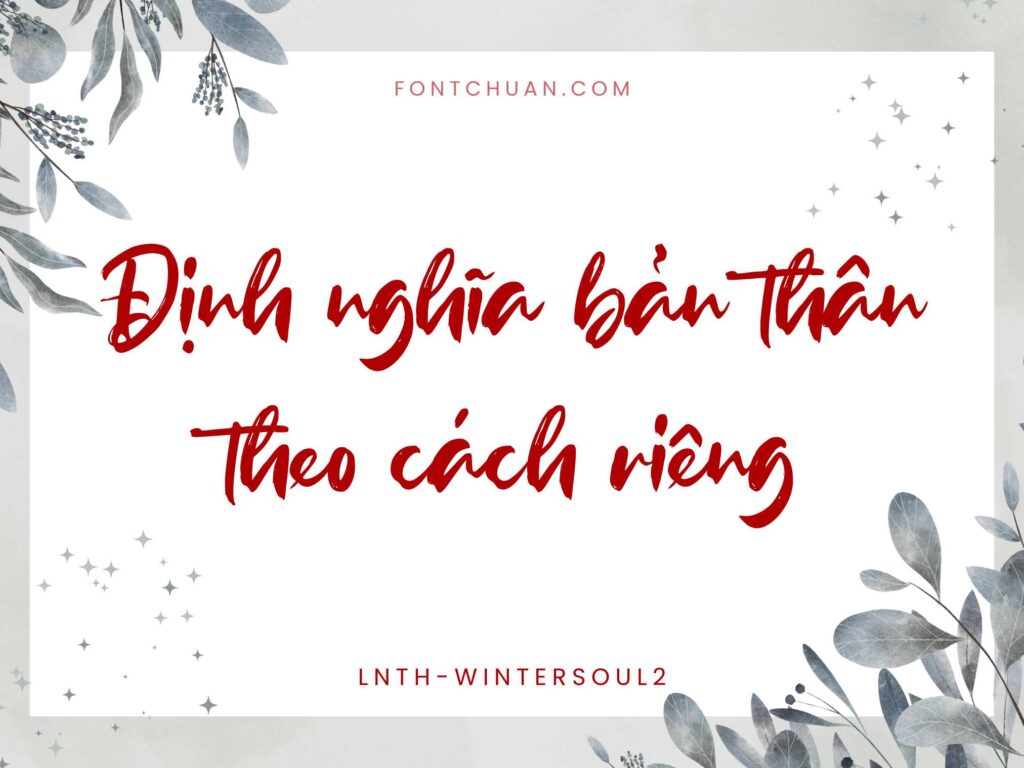
Font LNTH Wintersoul Việt Hóa
Font Wintersoul là một font chữ viết tay mang phong cách nghệ thuật, mềm mại và tinh tế, rất phù hợp với các thiết kế sáng tạo và lãng mạn. Được lấy cảm hứng từ những nét chữ thư pháp nhẹ nhàng, Wintersoul mang lại cảm giác thanh thoát, bay bổng và đầy nghệ thuật, thích hợp cho các thiết kế về mùa đông, Giáng sinh, lễ hội hoặc các sự kiện mang tính cá nhân.
Phiên bản này đã được Việt hóa bởi LNTH, hỗ trợ đầy đủ tiếng Việt cùng hơn 50 ngôn ngữ khác, giúp người dùng dễ dàng ứng dụng trong thiết kế quốc tế. Font Wintersoul được các thành viên Font Chuẩn sưu tầm và đăng tải nhằm đáp ứng nhu cầu tìm kiếm một font chữ mang phong cách mềm mại, lãng mạn và mang hơi hướng thư pháp hiện đại.
Về đặc điểm thiết kế, Wintersoul có những đường nét uốn lượn uyển chuyển, độ dày mỏng linh hoạt giúp tạo ra sự nhẹ nhàng và tự nhiên như chữ viết tay. Kiểu chữ này đặc biệt thích hợp để sử dụng trong typography nghệ thuật, thư mời, thiệp cưới, thiết kế logo, bao bì sản phẩm cao cấp hoặc các sản phẩm handmade.
Font Wintersoul được ứng dụng rộng rãi trong các sự kiện như Giáng sinh, Valentine, Thiệp cưới hoặc các dự án mang phong cách lãng mạn. Nó phù hợp với nhiều ngành nghề như quảng cáo, thiết kế thương hiệu, spa, thiệp cưới và trang trí sự kiện.